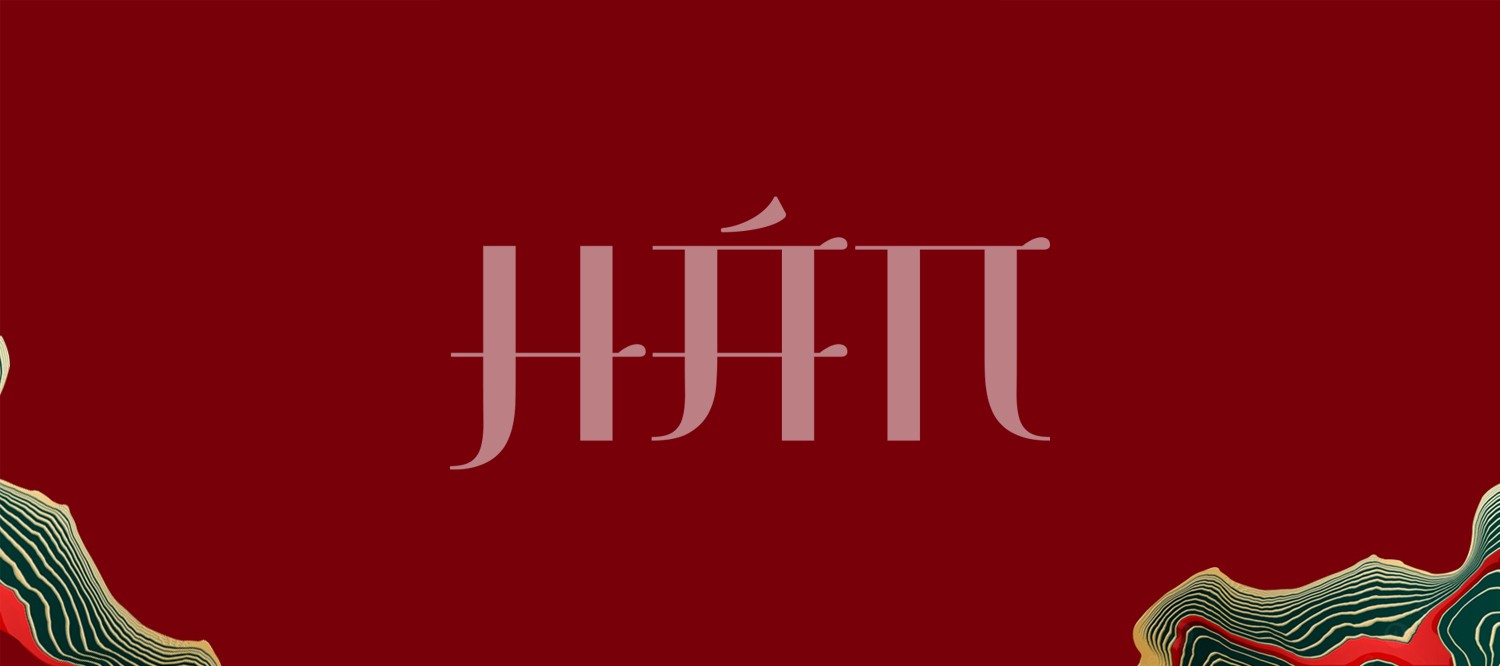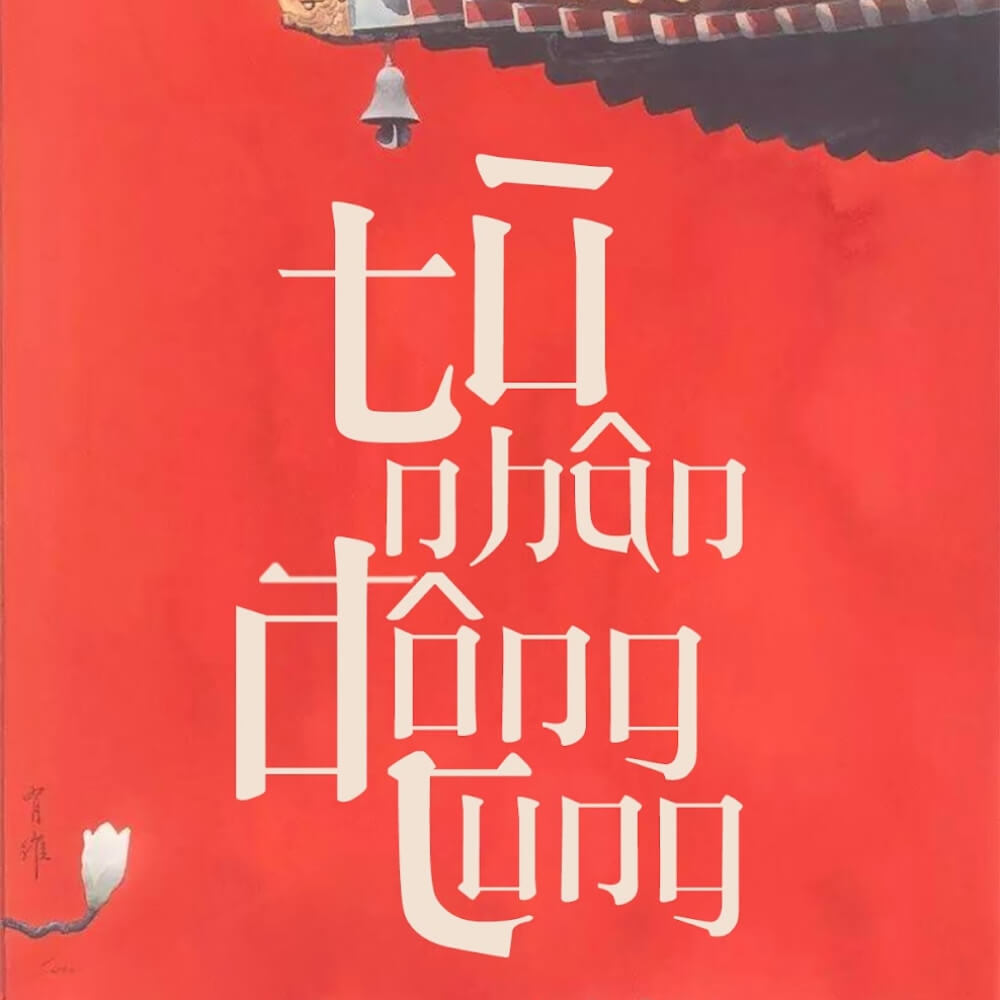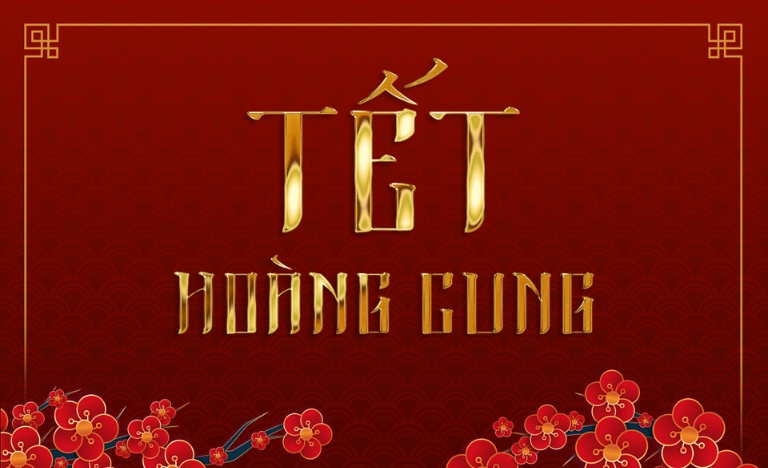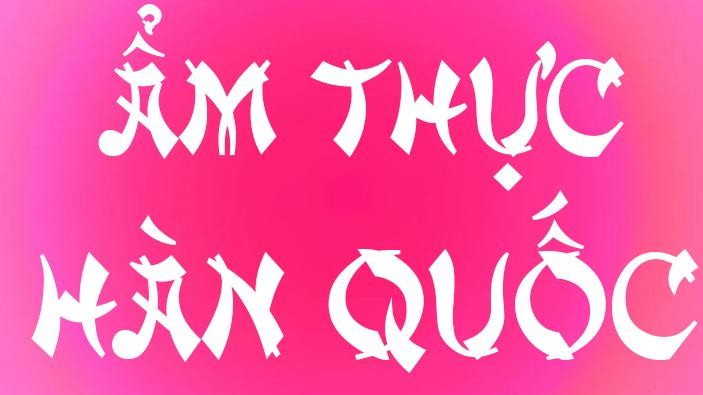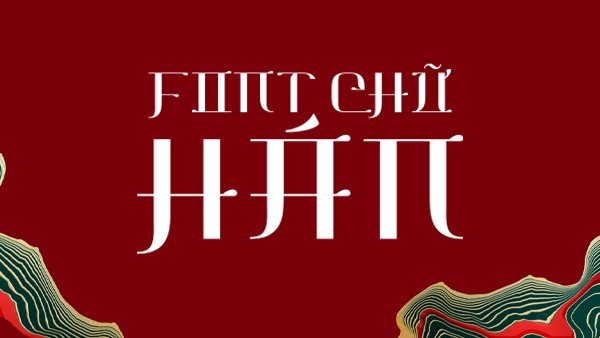
Trong các dự án kiến trúc mang phong cách truyền thống hoặc những không gian nghỉ dưỡng hướng đến vẻ đẹp hoài cổ, việc lựa chọn phông chữ đóng vai trò quan trọng để truyền tải linh hồn của tác phẩm. Font chữ Hán Việt hóa là bộ sưu tập các kiểu chữ mô phỏng cấu trúc của chữ Hán và chữ Nôm nhưng được tinh chỉnh để gõ được bảng chữ cái tiếng Việt.
Đặc điểm thẩm mỹ độc đáo của bộ font chữ Hán Việt hóa
Sức hút của dòng phông chữ này nằm ở cách mô phỏng các kỹ thuật viết bút lông kinh điển như lối chữ Khải, chữ Lệ hay chữ hành. Các nét chữ thường có cấu trúc vuông vức, vững chãi, tạo cảm giác trang trọng và cổ kính cho văn bản. Phiên bản font chữ Nôm Việt hóa đã được xử lý khéo léo để các dấu thanh tiếng Việt (huyền, sắc, hỏi, ngã, nặng) nằm gọn trong khung hình vuông của ký tự, giúp tổng thể trình bày không bị rời rạc hay lỗi nhịp so với cấu trúc nguyên bản.
Sự ổn định về mặt thị giác của dòng font này còn giúp người xem cảm nhận được sự giao thoa giữa quá khứ và hiện tại. Thay vì sử dụng những phông chữ Latinh hiện đại có phần mảnh mai, các nét chữ dày và dứt khoát của phong cách Hán Nôm tạo nên điểm nhấn mạnh mẽ trên các bề mặt vật liệu tự nhiên như gỗ, đá hoặc gạch gốm. Đây là phương án hiệu quả để nâng tầm giá trị cho các công trình có xu hướng bảo tồn văn hóa hoặc kiến trúc Zen tự tại.
| Phân loại phong cách | Hán Nôm / Brush / Oriental Style |
| Mục đích phù hợp | Bảng hiệu hoài cổ, Poster lễ hội, Decor |
Lời khuyên thiết kế: Khi sử dụng font chữ Hán Việt hóa, bạn nên ưu tiên các tông màu trầm như đen mực tàu, đỏ son hoặc vàng đồng trên nền vật liệu tối màu. Việc phối hợp cùng một phông chữ không chân tối giản cho phần thông tin phụ sẽ giúp bản thiết kế đạt được sự cân bằng, tránh cảm giác nặng nề cho người xem.
03 Ứng dụng đưa font chữ Hán Việt hóa vào thực tế kiến trúc
Nhờ diện mạo giàu tính biểu tượng và sự trang nghiêm, bộ phông chữ này mang lại giá trị cao trong khâu trang trí các công trình xây dựng có yếu tố truyền thống:
- Bảng nhận diện cho Homestay & Khu nghỉ dưỡng Zen: Những nét chữ giả cổ rất ăn ý khi xuất hiện trên biển hiệu bằng gỗ thịt hoặc đá tự nhiên tại các khu nhà lắp ghép nghỉ dưỡng. Điều này giúp du khách cảm nhận được không gian tĩnh tại ngay từ khi bước chân vào công trình.
- Trang trí không gian nội thất văn hóa: Bạn có thể dùng font này để thiết kế các bức hoành phi, câu đối hoặc decal dán tường tại phòng khách, khu vực trà đạo nhằm tạo điểm nhấn đầy thẩm mỹ và chiều sâu cho không gian sinh hoạt.
- Hồ sơ thuyết minh dự án bảo tồn: Sử dụng font chữ nôm Việt hóa cho các tiêu đề chương hoặc sơ đồ vị trí giúp hồ sơ trở nên chuyên nghiệp, thể hiện sự am hiểu và tôn trọng của đơn vị thiết kế đối với bối cảnh lịch sử của dự án.
03 Lưu ý để trình bày phông chữ Hán Nôm hài hòa và sang trọng
Để khai thác hiệu quả vẻ đẹp của dòng font đặc thù này mà không làm rối mắt người đọc, người thiết kế nên lưu tâm một số kinh nghiệm sau:
- Kiểm soát mật độ chữ: Do cấu trúc chữ Hán Nôm thường dày và chiếm không gian, bạn nên nới rộng khoảng cách giữa các chữ cái (tracking) và khoảng cách dòng. Việc để các ký tự quá sát nhau sẽ khiến văn bản bị bết dính và khó nhận diện mặt chữ.
- Hạn chế dùng cho đoạn văn dài: Chỉ nên sử dụng phông chữ này cho tiêu đề, slogan hoặc các câu trích dẫn ngắn. Việc lạm dụng cho toàn bộ nội dung thuyết minh kỹ thuật sẽ gây mỏi mắt và làm giảm tính chuyên nghiệp của bản vẽ.
- Lựa chọn kích thước hiển thị: Font phong cách Hán Việt phát huy hiệu quả thị giác tốt ở kích thước trung bình đến lớn. Ở kích thước quá nhỏ, các chi tiết nét cọ mô phỏng có thể bị nhòe, gây khó khăn cho việc quan sát từ xa.